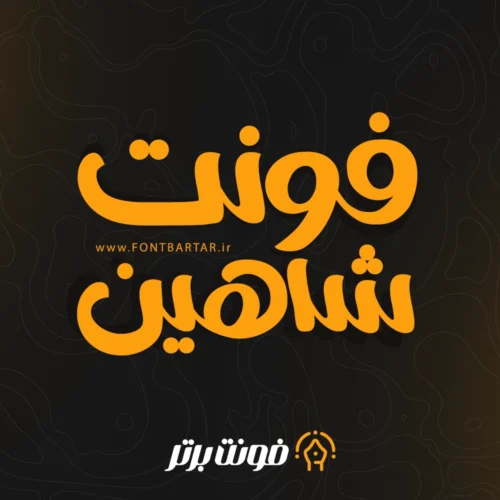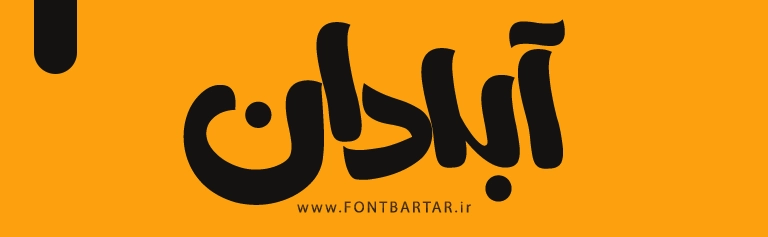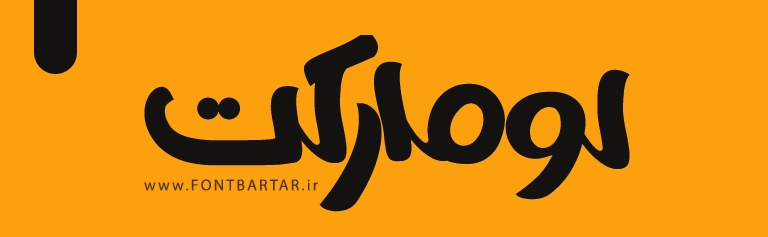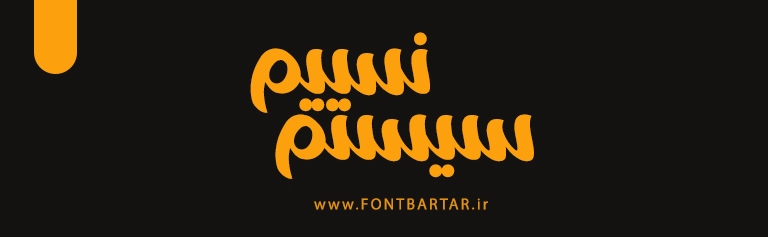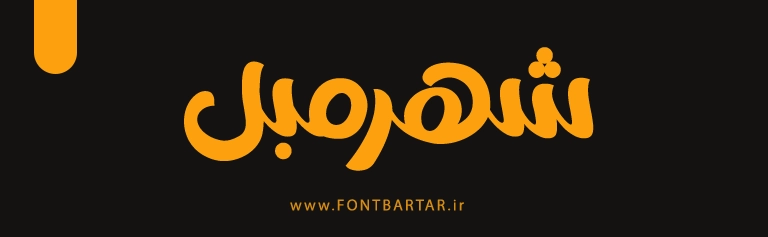
فونت جدید شاهین
Shahin Font
دانلود فونت فارسی شاهین – فونت دست‌نویس خاص برای طراحی مدرن
فونت شاهین یکی از جدیدترین فونت‌های فارسی با حالتی دست‌نویس، روان و نمایشی است که برای طراحانی که به دنبال فونت خاص و پرانرژی هستند، یک انتخاب بی‌نظیر محسوب می‌شود. فونت جدید فارسی با ترکیب خطوط نرم و ضربات جسورانه، مناسب طراحی کاور، لوگوتایپ، تیتر تبلیغاتی، پوستر و پست‌های شبکه اجتماعی است.
⭐ ویژگی‌های فونت جدید شاهین
• طراحی منحصر‌ به‌ فرد و خلاقانه با حالتی دست‌ نویس
• ایده‌آل برای طراحی عنوان و نوشته‌های گرافیکی
📌 موارد استفاده پیشنهادی فونت شاهین
• طراحی پوستر تبلیغاتی و هنری
• فونت کاور اینستاگرام
• لوگوتایپ برندهای خلاق و جوان‌پسند
• بنرهای دیجیتال برای شبکه‌های اجتماعی
• طراحی جلد کتاب و نشریات بصری
• استفاده در تیزرهای ویدیویی یا تایپوگرافی متحرک
1. فونت شاهین برای طراحی لوگو مناسب است؟
بله، با توجه به استایل خاص و نمایشی آن، برای طراحی لوگوهای تایپوگرافی بسیار مناسب است.